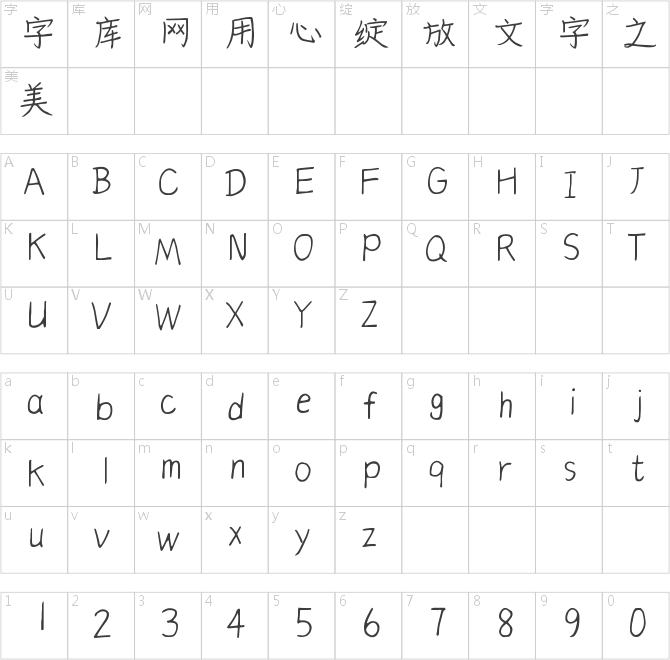
倉(cāng)耳同桌體
倉(cāng)耳同桌體字體字庫(kù)是一款讓人賞心悅目、百看不厭的中文字體,適合各類廣告和產(chǎn)品包裝設(shè)計(jì)應(yīng)用,字體大小3.71MB,格式為ttf字體,上傳用戶是/zyj【GF】,作者/版權(quán)方為倉(cāng)耳字庫(kù)